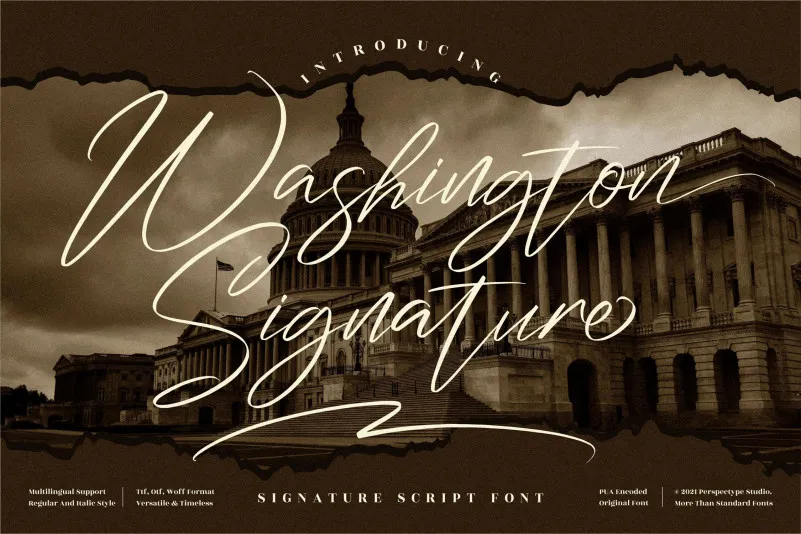
Washington Signature Font – Download Grátis
Esta é uma fonte escrita a mão com traços leves que adicionará um toque sofisticado e único ao seu próximo projeto de design. Inspirada na elegância das escritas manuscritas, essa fonte vem com um impacto poderoso e encantador, certamente transformando qualquer projeto em uma experiência visual única. Perfeita para criar trabalhos finos e luxuosos, esta fonte do Washington Signature é perfeitamente adaptável a várias necessidades de design. Seja você criando cartazes de eventos especiais, design de embalagens sofisticadas ou até mesmo texturas digitais, essa fonte trará um toque especial à sua obra. Sem dúvida, vale cada centavo para designers que buscam uma aparição de luxo em seus projetos.